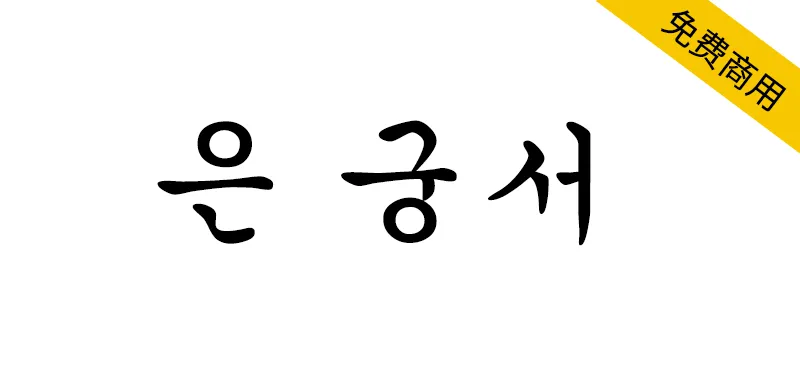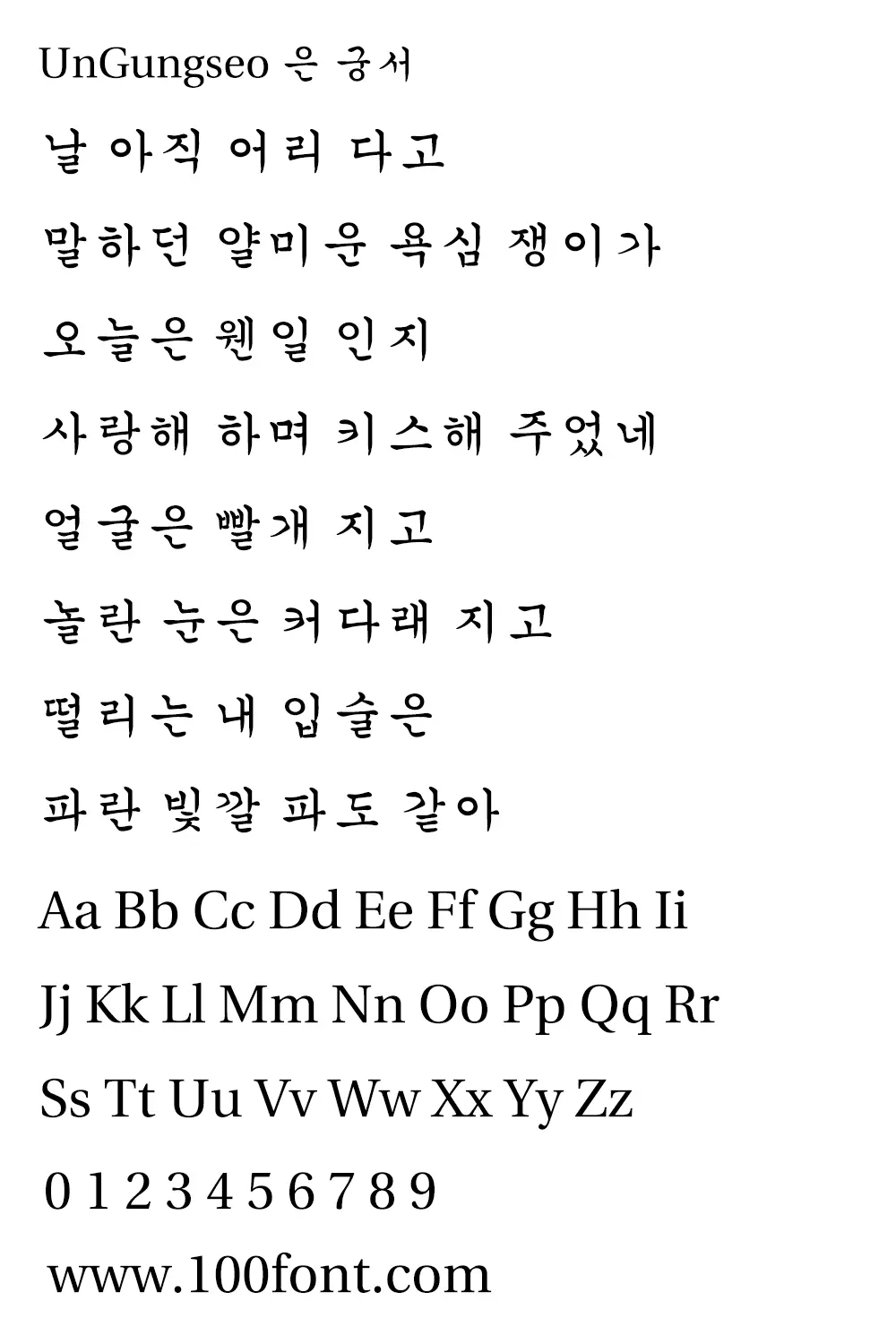
UnGungseo楷體(은 궁서)是韓國Un開源系列字體中的其中一款,韓國Un系列字體是由@Koaunghi Un於1998年以HLaTeX type1製作而成,作者在20世紀90年代末製作type1字體用於韓國的Tex(JLaTex[1]),並以GNU GENERAL PUBLIC LICENSE授權許可進行發佈。於2003年,由@Won-kyu Park使用FontForge(PfaEdit)轉換成ttf文件進行發佈。
注意:這款字體支持的簡體中文字數比較少,不適用用於簡體中文場景,適用於韓語和繁體。